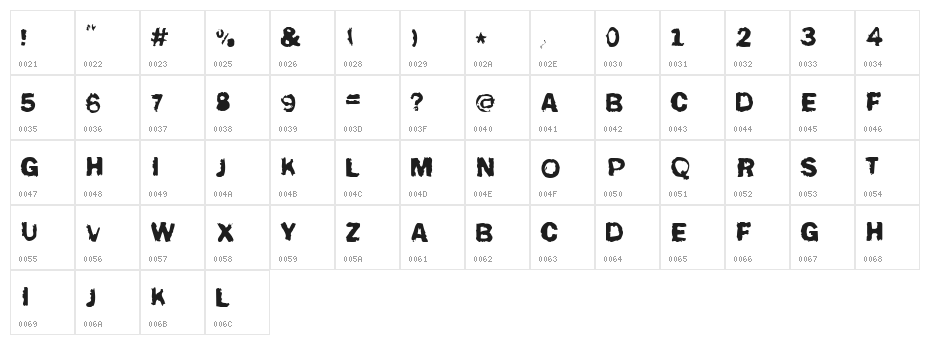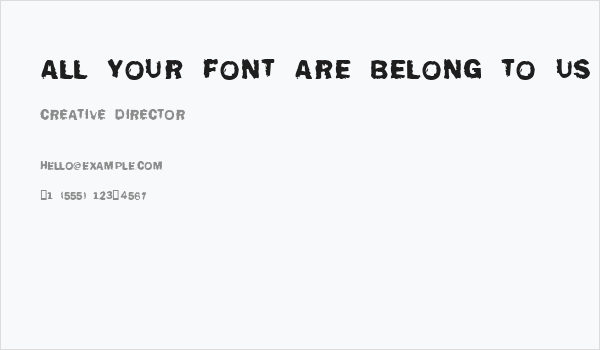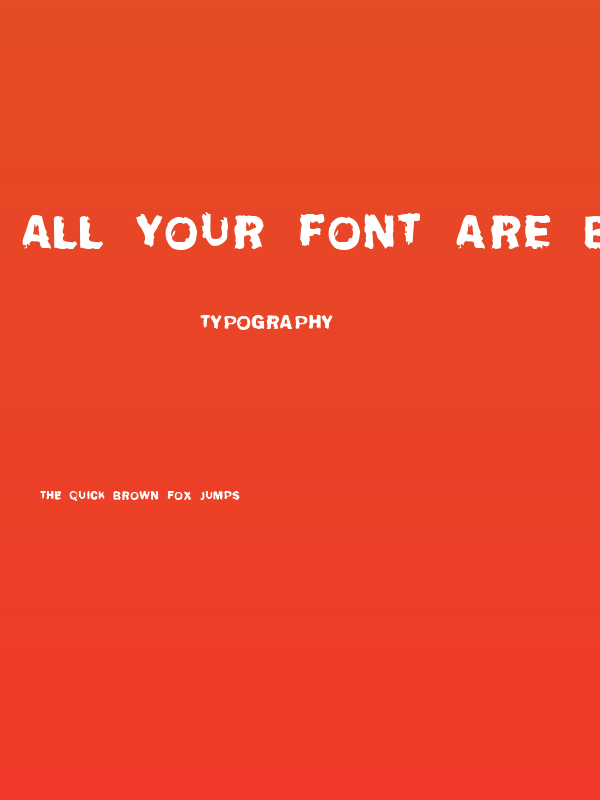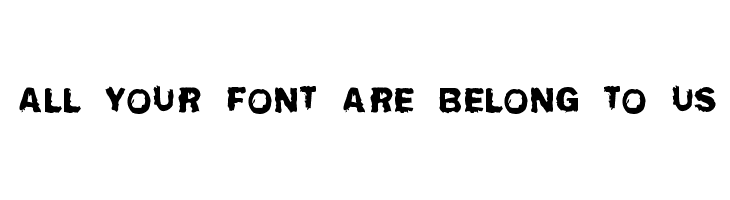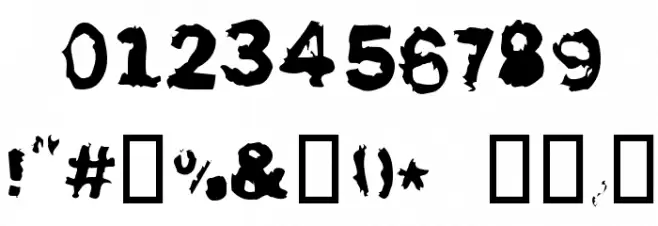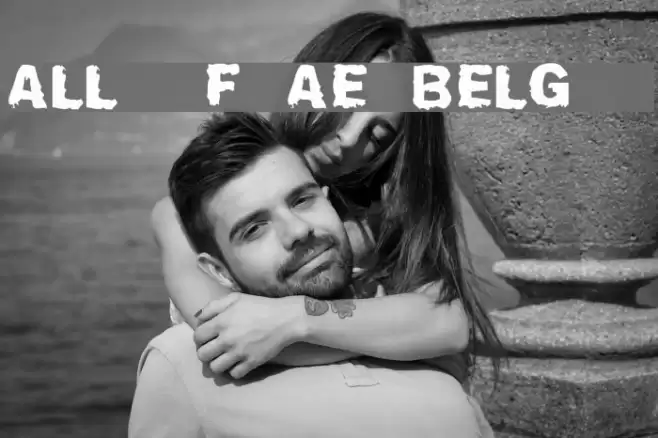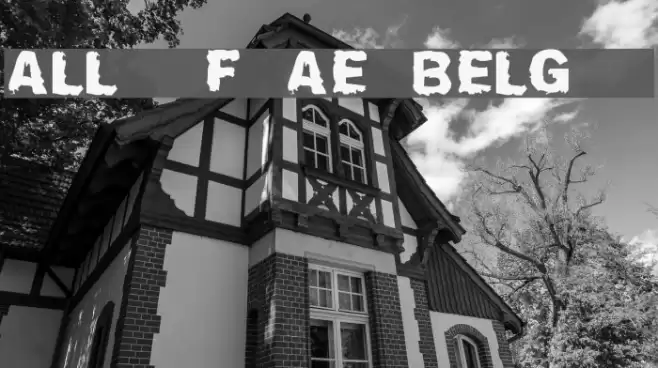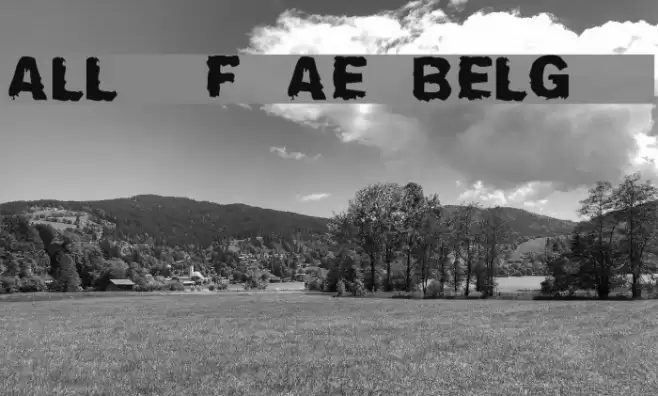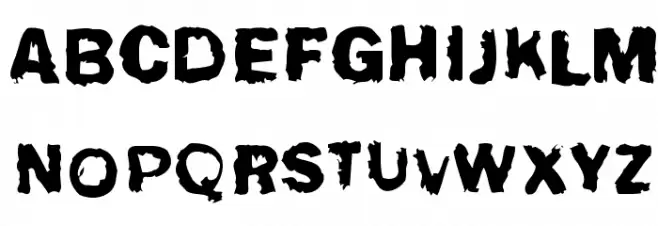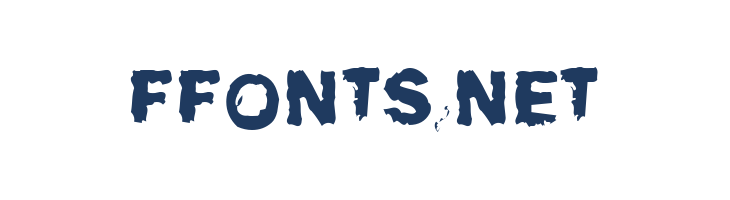
All your font are belong to us Font
| Stil general | Grunge, Edgy |
| Proiecte propuse | Ideal for album covers, posters, urban-themed designs, and any project needing a gritty, bold statement. |